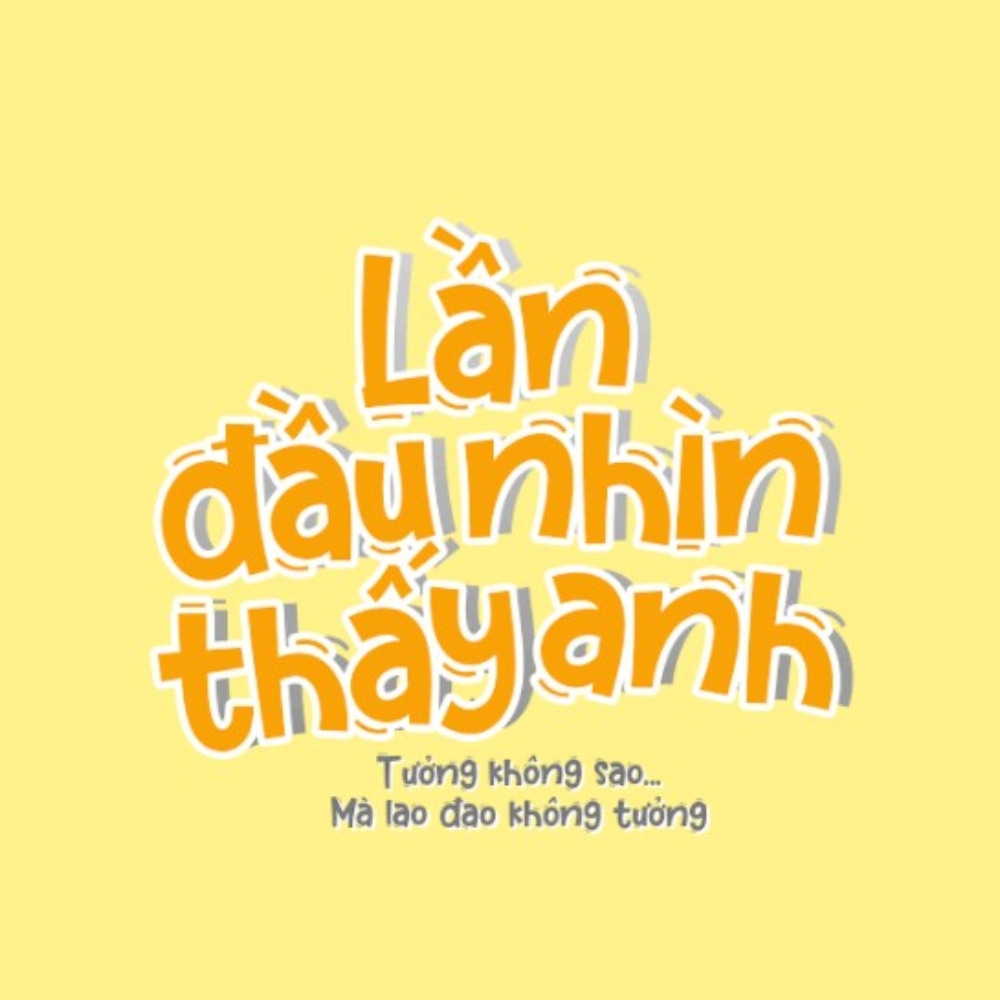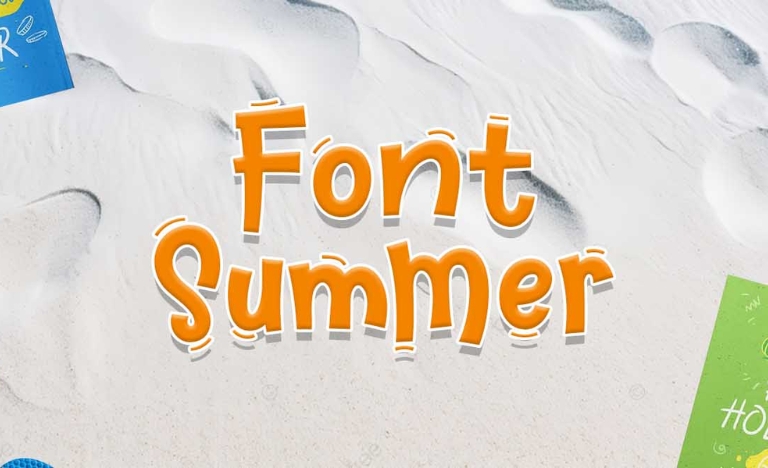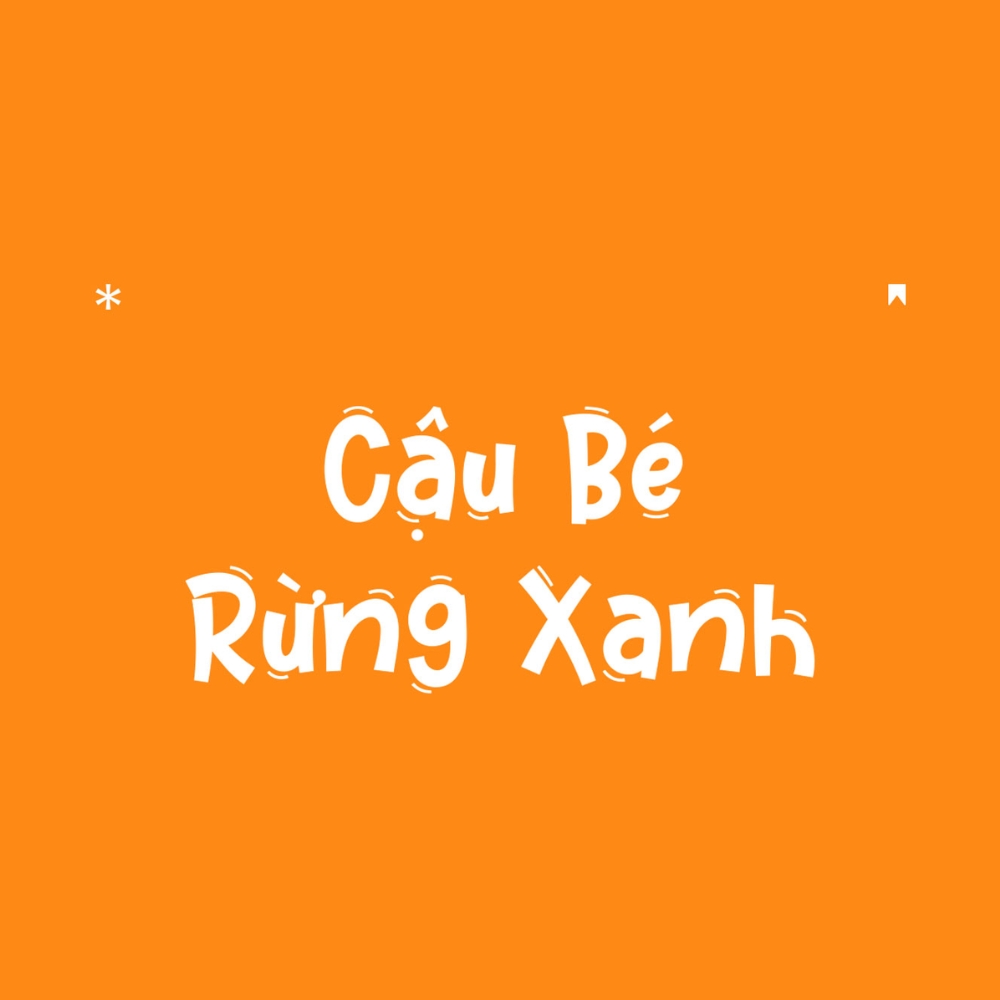
Nhiều designer khi tải font Việt hoá MTD Summer Show thường gặp tình trạng lỗi hiển thị tiếng Việt, mất dấu hoặc sai tỷ lệ ký tự khi gõ các chữ có dấu như “ư, ơ, đ” trong Photoshop hay Illustrator. Hệ quả là bản thiết kế bị đứt gãy thẩm mỹ, tốn hàng giờ chỉnh sửa thủ công và dễ gây sai sót khi in ấn hàng loạt trên các ấn phẩm quà tặng.
04 lưu ý khi dùng font MTD Summer Show trong in ấn
Làm việc với font chữ có nét dày và bo tròn như font việt hóa mtd summer show đòi hỏi sự cẩn trọng đặc biệt trong khâu xuất file in. Để bản in đạt độ hoàn mỹ nhất, bạn cần lưu ý các vấn đề sau:
• Quy tắc Create Outlines: Trước khi gửi file đến xưởng in, bạn bắt buộc phải chuyển đổi font chữ thành dạng vector (nhấn Ctrl + Shift + O trong Illustrator). Việc này giúp tránh lỗi máy in không đọc được font lạ và tự động thay thế bằng font mặc định làm hỏng thiết kế.
• Điều chỉnh Kerning (khoảng cách chữ): Do các nét chữ của Summer Show khá mập, nếu để khoảng cách quá gần, mực in có thể bị loang trên các chất liệu thấm như túi giấy Kraft. Hãy chủ động nới rộng khoảng cách chữ thêm khoảng 5% để đảm bảo độ sắc nét.
• Giới hạn kích thước tối thiểu: Với các dòng quà tặng có bề mặt nhỏ như bút ký hay bình giữ nhiệt, không nên để font chữ này ở size dưới 8pt. Các chi tiết rỗng bên trong chữ “a, o, e” dễ bị lấp đầy bởi mực hoặc đường khắc laser.
• Kiểm tra hệ màu in ấn: Luôn chuyển đổi file thiết kế sang hệ màu CMYK trước khi xuất file. Font chữ có màu sắc rực rỡ trên màn hình RGB thường sẽ bị xỉn màu hơn khi in thực tế nếu không được hiệu chỉnh thông số màu chuẩn xác.
Font chữ hoạt hình MTD Summer Show việt hóa tươi sáng, phù hợp thiết kế vui nhộn
Summer font việt hóa mang phong cách trẻ trung, thích hợp chủ đề mùa hè